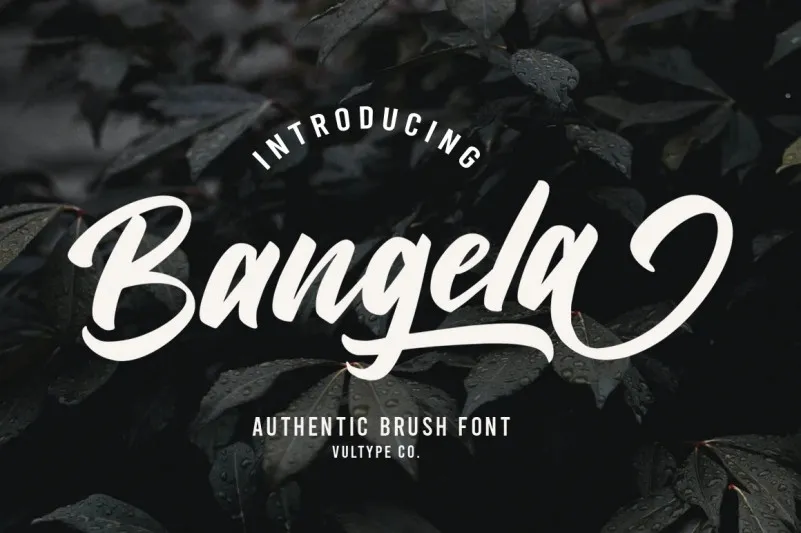
Bangela Font – Download Grátis
A Bangela Font é uma elegante fonte escrita à mão inspirada no estilo moderno vintage e retro, combinado com um ar tradicional americano antigo. Essa fonte transmite clareza e beleza ao mesmo tempo, tornando-a perfeita para criar letra desenhada. Além disso, Vultype Co., o designer da fonte, incluiu uma série de caracteres em estilo Swash como um benefício adicional, proporcionando aos criadores de design a facilidade de adicionar elementos únicos e atraentes ao seu trabalho. Essa combinação faz da Bangela Font um recurso indispensável para designers que buscam transpor letras desenhadas com graça e simplicidade, deixando qualquer projeto à sua disposição mais único e moderno.